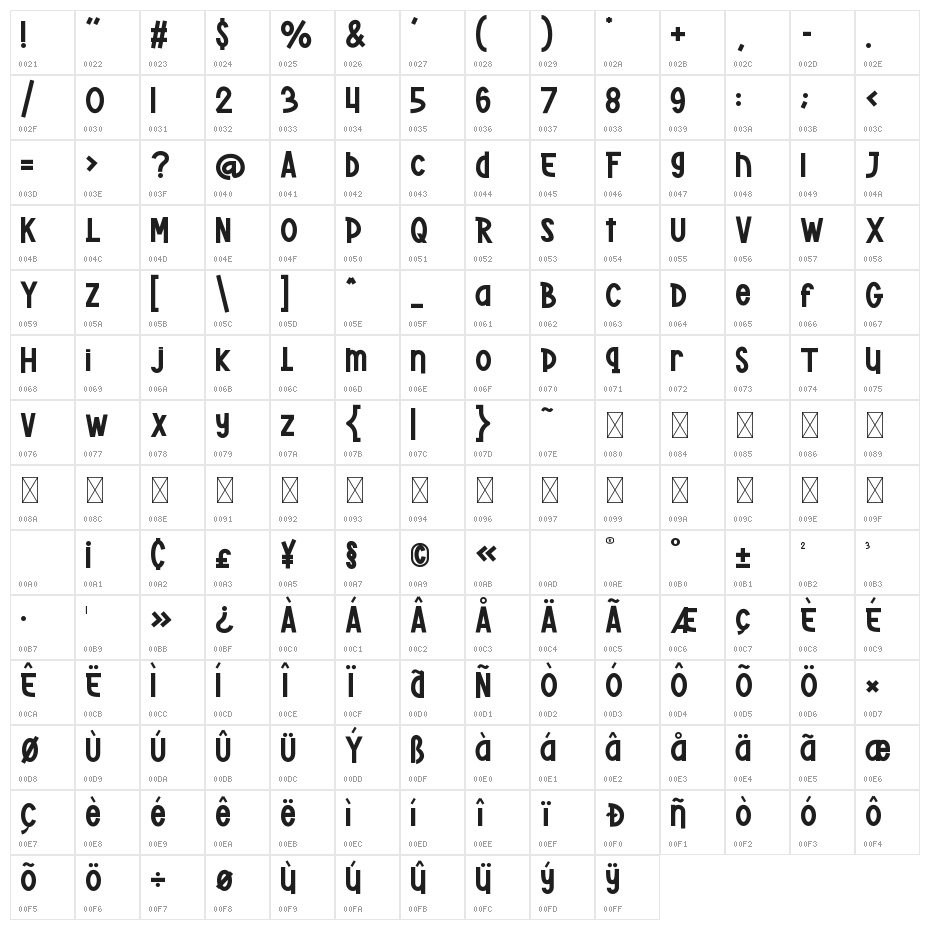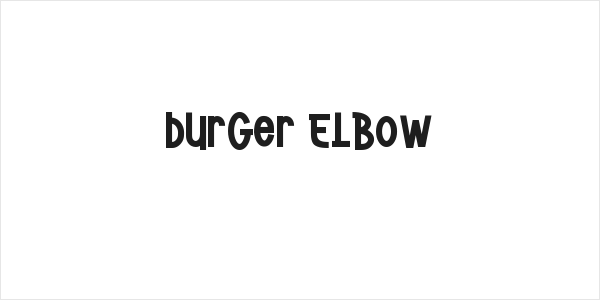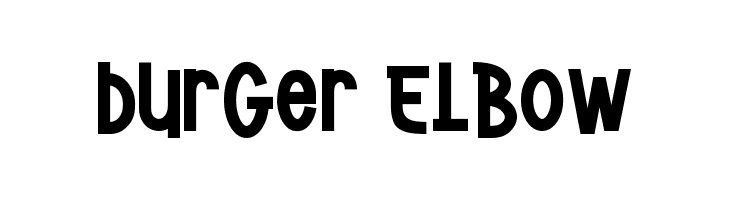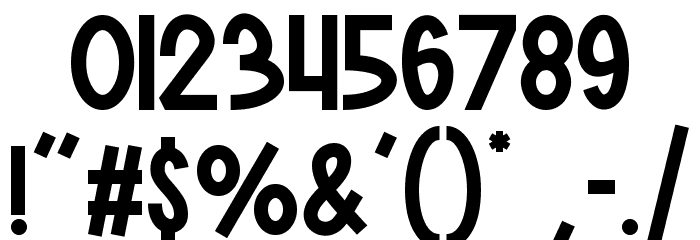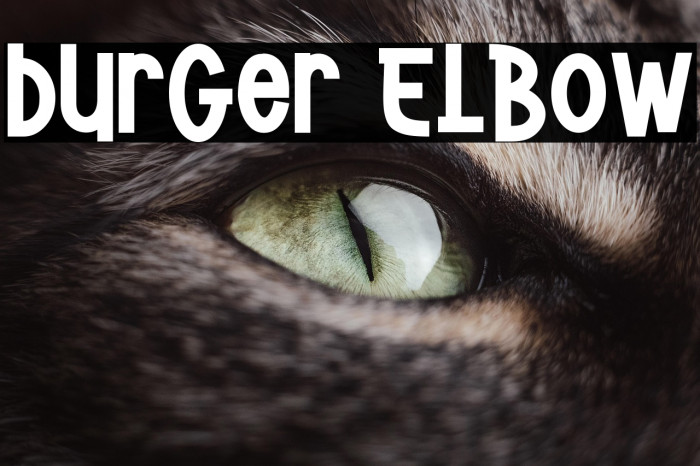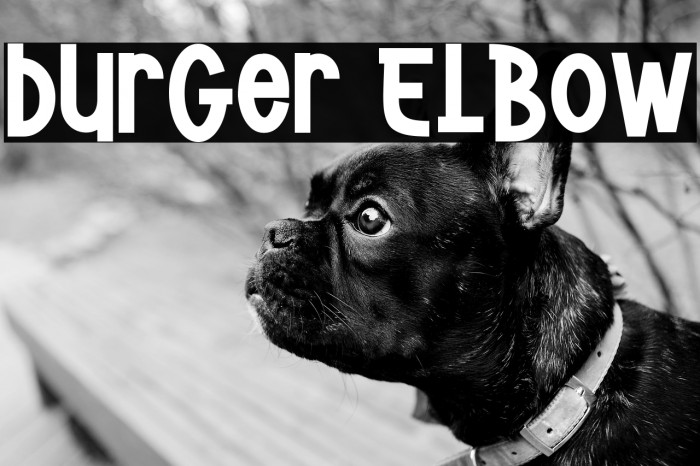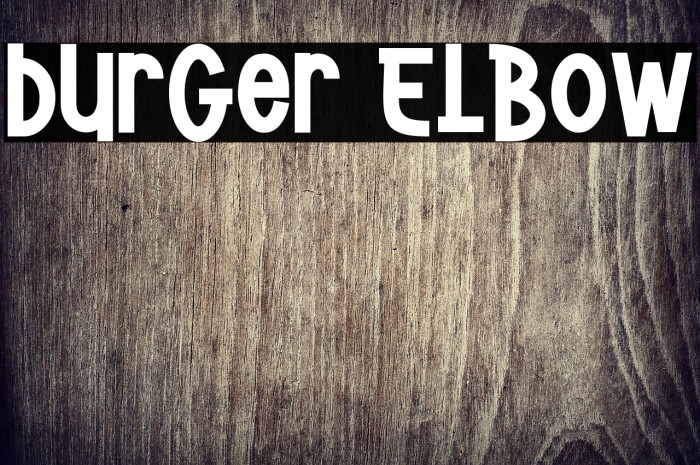
Burger Elbow Font
| Estilo general | Playful, Modern |
| Proyectos propuestos | Ideal for children's books, playful branding, posters, and creative advertisements. |